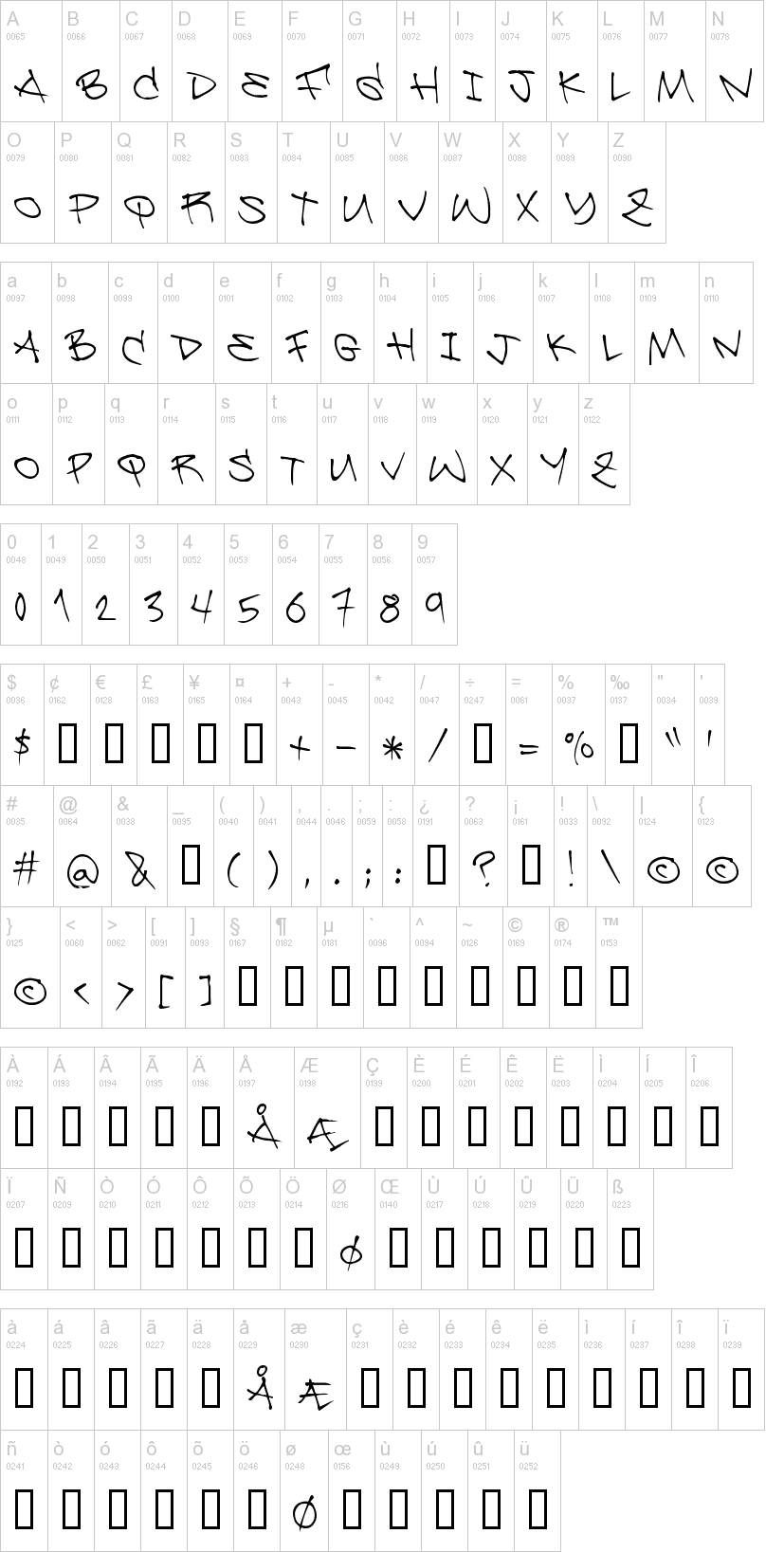
Be Aggressive 是一款专为英文设计的演示字体。它具有现代感,大胆的设计,以及细节丰富的字形。它的字形具有良好的可读性,并且可以提供出色的视觉效果。Be Aggressive 字体适合用于报纸、网页、海报、广告和其他宣传材料的设计中。内容介绍
Be Aggressive是一款非常不错的手写艺术字体,具有很好的视觉感,适合于文化类的宣传设计、商业类品牌的广告和产品包装设计以及个性化文字排版等较多场景。